相模原市による視覚で伝えるSDGs UDフォントを使った情報発信に取り組み -モリサワの協力で職員向け研修を実施-
相模原市では、弱視や文字の読み書きに課題がある方などへの配慮と効果的な情報発信を目的に、モリサワが提供する55書体のUDフォントを市職員用の一部パソコンで使用できるようにしたほか、チラシやポスターなどのデザイン・レイアウト研修の実施を2022年8月10日に発表した。
研修をふまえ、UDフォントの更なる活用によりSDGsの理念である「誰一人取り残さない社会」の実現を目指して情報発信を進めていく。
▼相模原市SDGs特設サイトでもUDフォントを採用。
市役所内で視覚的にSDGsを発信
市役所内の232課・機関において、業務に関連が深いSDGsのゴールを課名表示板に表示している。
この表示は、来庁者だけでなく、職員自身への普及啓発を推進することも目的としている。
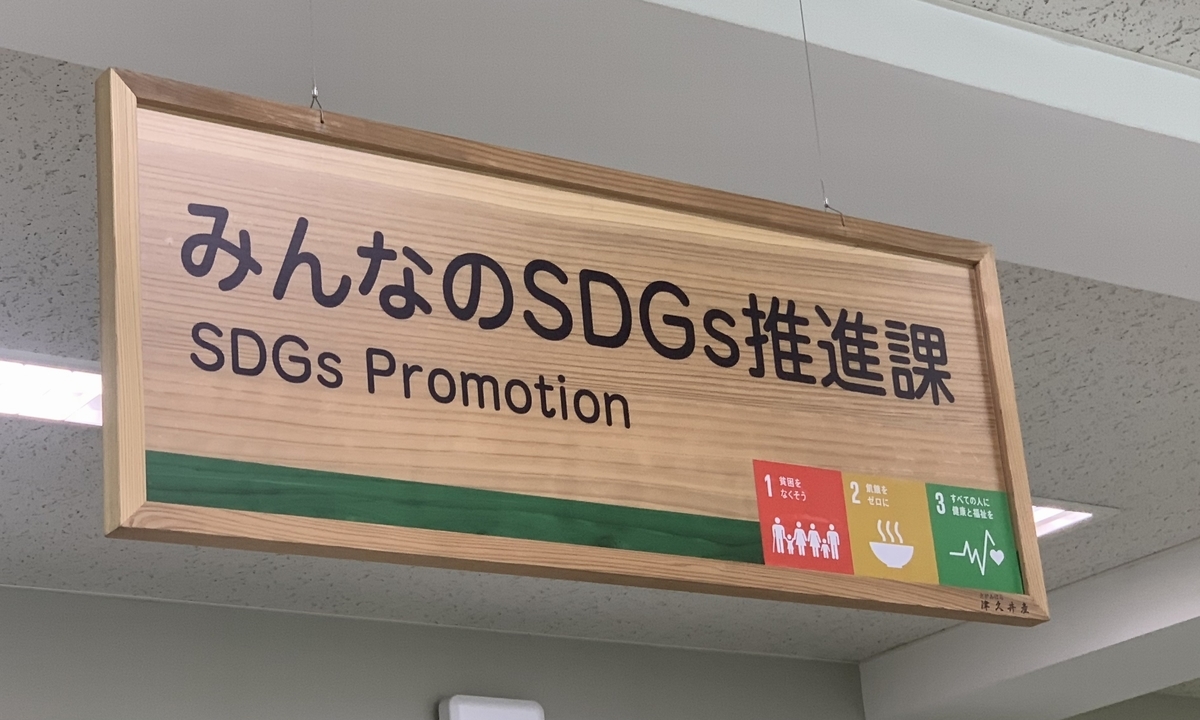
UDフォントの導入について
UDフォント(ユニバーサルデザインフォント)とは、「分かりやすく」「読みやすく」「読み間違えにくい」をコンセプトにデザインされた文字のことで、相模原市では、令和4年4月より「公共団体向けUDフォントプラン」を市職員用の一部パソコンで導入した。
※Windows10 ver.1809 から標準搭載となったUDフォント10書体については、市の全職員のパソコンに導入している。
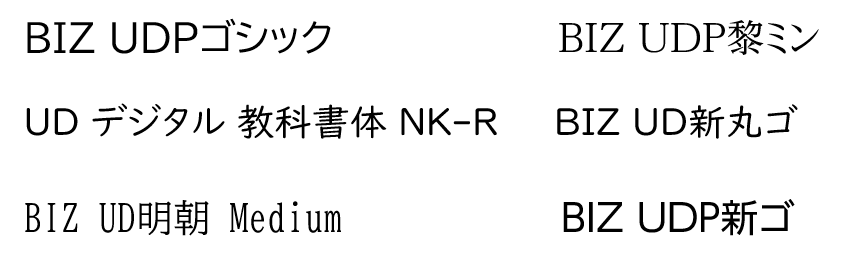
デザイン・レイアウト研修について
モリサワの野村氏を講師に招き、7月22日にオンラインで研修を実施した。
受講者は、あらかじめUDフォントやレイアウトについてのレクチャー動画を視聴し、職員が実際に使用している文書をリメイク。研修では、受講者がリメイクしたチラシを題材に、適切な行間やフォントの選択など、フィードバック。
デザインの悩みなどもその場でアドバイスをいただき、UDフォントの活用とレイアウトの工夫により、より分かりやすく、より一層思いが届く情報発信が可能になることを学んだ。